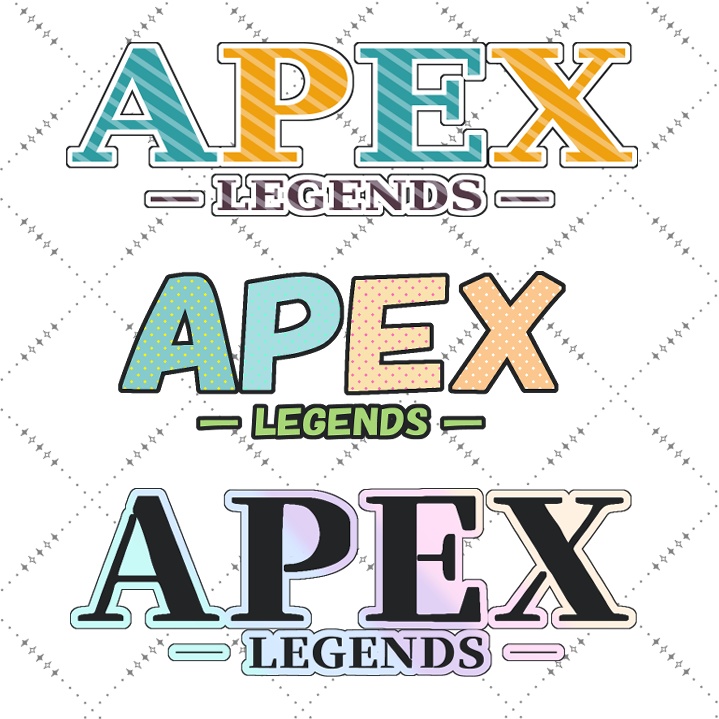
sayachonchi【素材】APEXフォントDigital0 JPYFree Downloadapex_斜線ハイライト.png (113 KB)Free Downloadapex_ドット.png (66.3 KB)Free Downloadapex_パステル.png (123 KB)apex_斜線ハイライト.pngapex_ドット.pngapex_パステル.pngAbout GiftAPEXフォント素材3種です 上から ▶斜線ハイライト ▶ドット ▶パステル となっております。 ダウンロードの際は、名前をご確認の上お願いいたします。 また、ダウンロード際はいいねの方をよろしくお願いいたします。 他にも無料素材やイラスト依頼の出品も行っております。 ご縁がありましたら、ぜひ、ご利用ください。 ※ご依頼の際はDMにてお問合せください。sayachonchiVisit FANBOX!Materials (Other)【背景】VALORANT【素材】sayachonchi200 JPY~Logos【ロゴ】VALORANT【素材】sayachonchi0 JPYMaterials (Other)【背景】APEX【素材】sayachonchi0 JPYMaterials (Other)【おはツイ】桜舞う素材【無料配布】sayachonchi0 JPYMaterials (Other)【全8種】チェック柄背景素材sayachonchi400 JPY~Logos【全6種】参加型ロゴ素材sayachonchi200 JPYGraphics【スタンプ】猫型ふきだしスタンプsayachonchi200 JPY~Illustration (Other)【スタンプ】全3種【1個200円】sayachonchi200 JPY~Illustration (Other)▽2等身立ち絵sayachonchi1,000 JPY~Materials (Other)【無料】サムネイル素材sayachonchi0 JPYMaterials (Other)【背景素材】サムネイル用【全5種】sayachonchi0 JPYMaterials (Other)【配信者向け】参加型ロゴ【素材配布】sayachonchi100 JPYMaterials (Other)【背景素材】APEX用【全4種】sayachonchi0 JPYMaterials (Other)【素材】VALORANT用背景【素材】sayachonchi0 JPYIllustration (Other)むにゅ顔【イラスト依頼】sayachonchi250 JPY~Materials (Other)【背景】花チェック柄【素材】sayachonchi0 JPYMaterials (Other)【素材】和風参加型ロゴ【配布】sayachonchi0 JPYMaterials (Other)【スタンプ】参加希望【素材】sayachonchi0 JPYGraphics【量産型】幽霊風スタンプsayachonchi200 JPY~See More